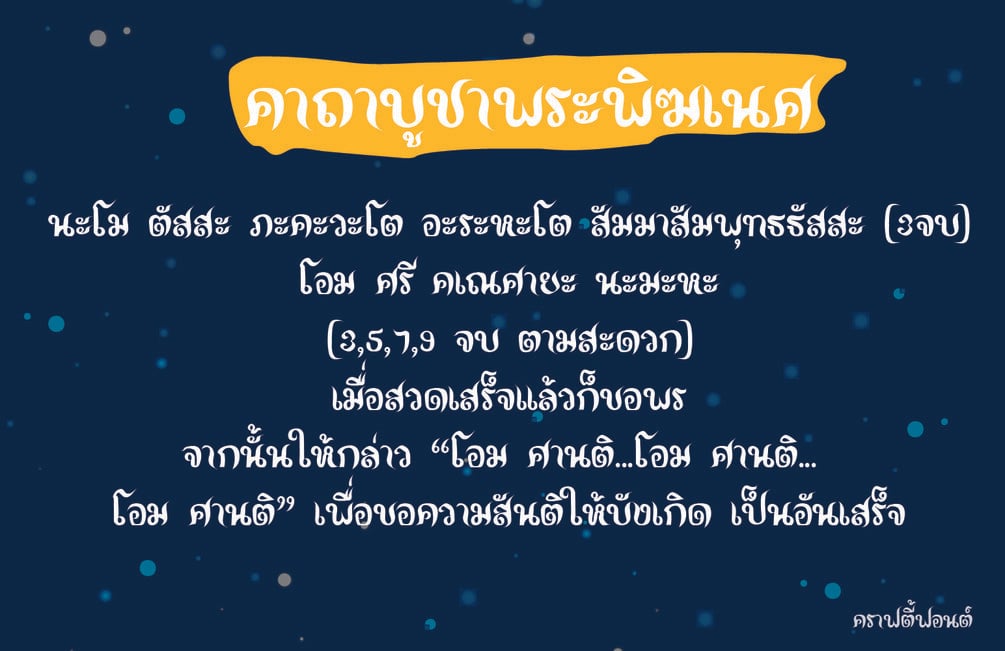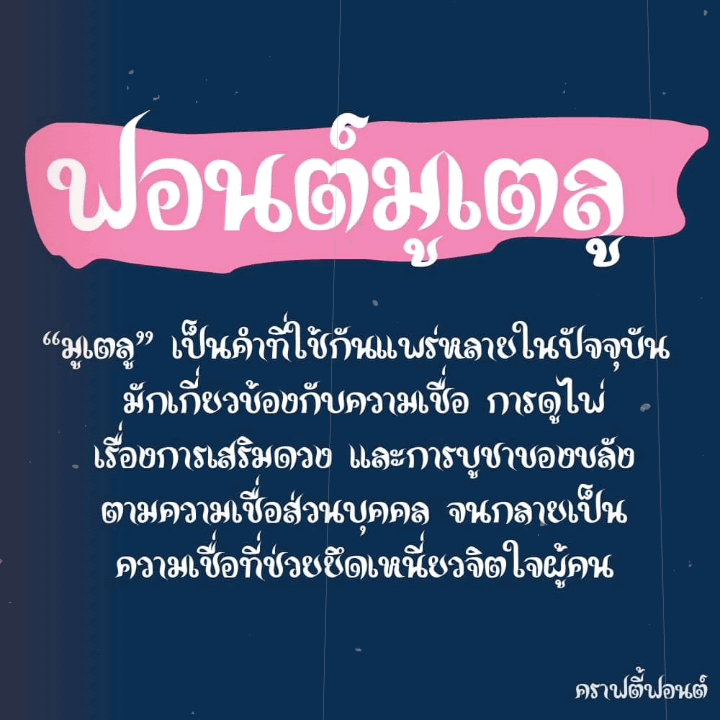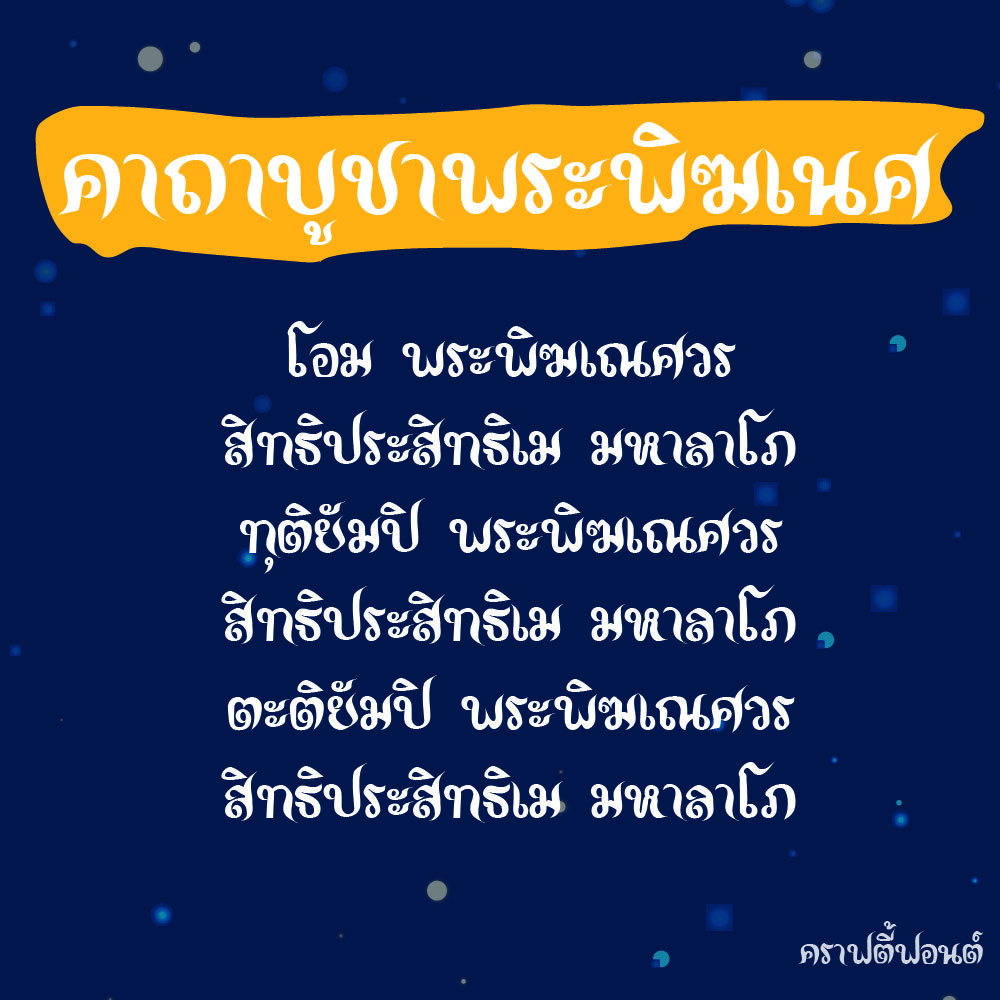
Mutelu Font (ฟอนต์มูเตลู)
ฟอนต์ลายเส้นโบราณแต่ใส่หัวทำให้ดูน่ารัก ตามสไตล์ crafty font มากยิ่งขึ้น! พิมพ์ได้เฉพาะภาษาไทยนะคะ ภาษาอังกฤษไม่มีค่า แต่ตัวเลขสัญลักษณ์บวกลบคูณหารมีครบค่า หวังว่าทุกคนจะชอบนะคะ ❤️